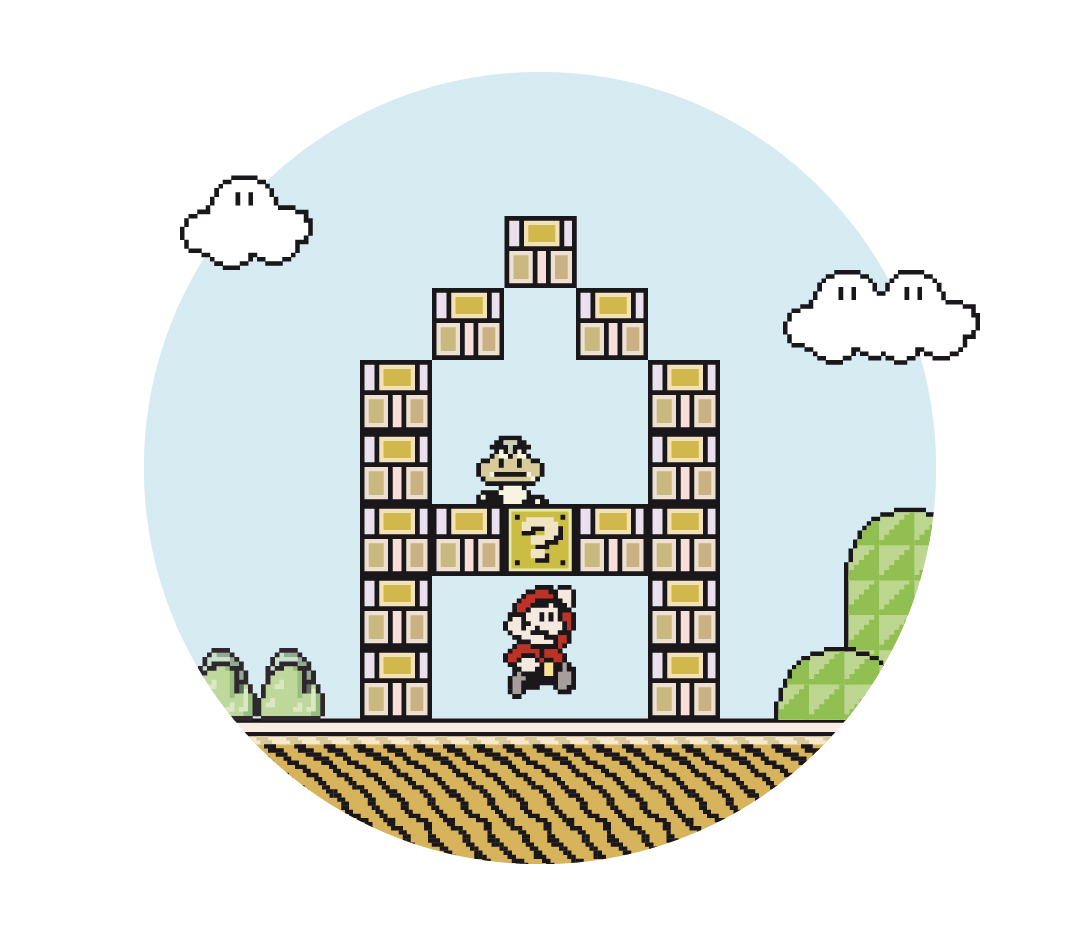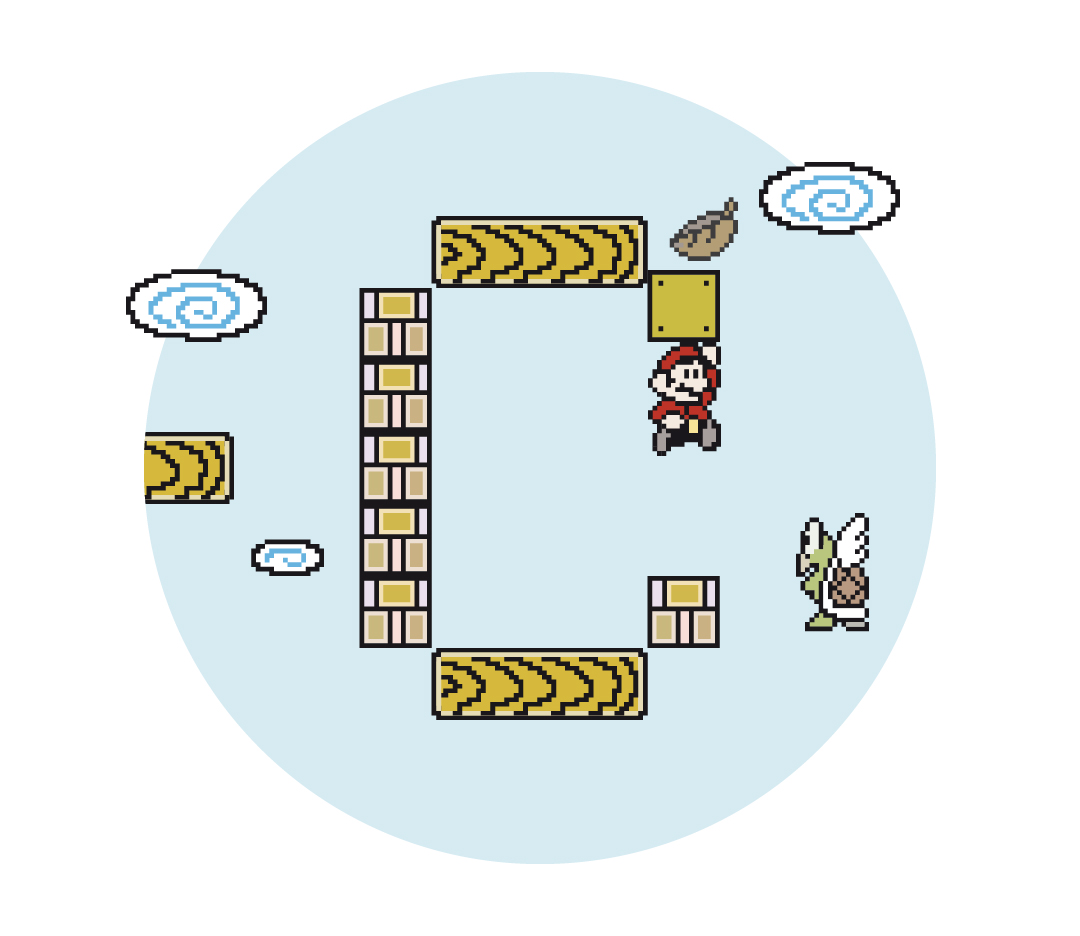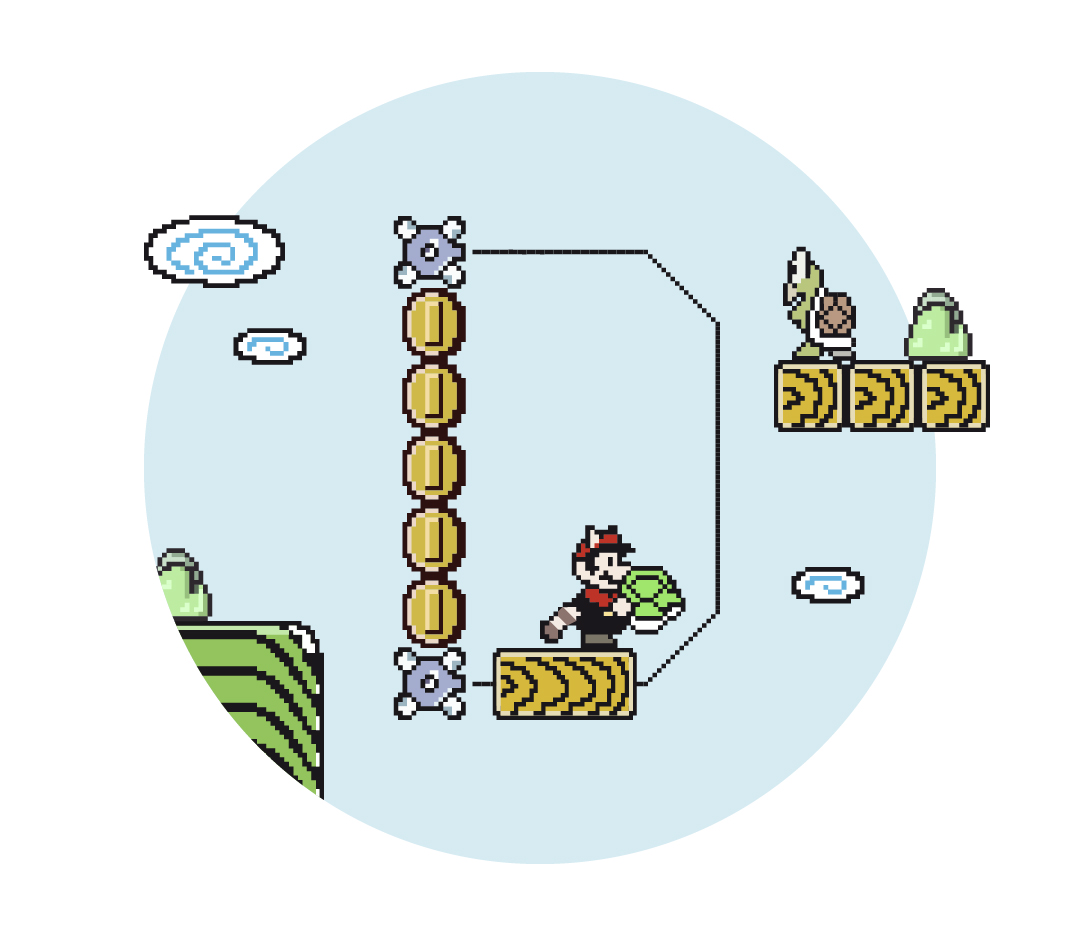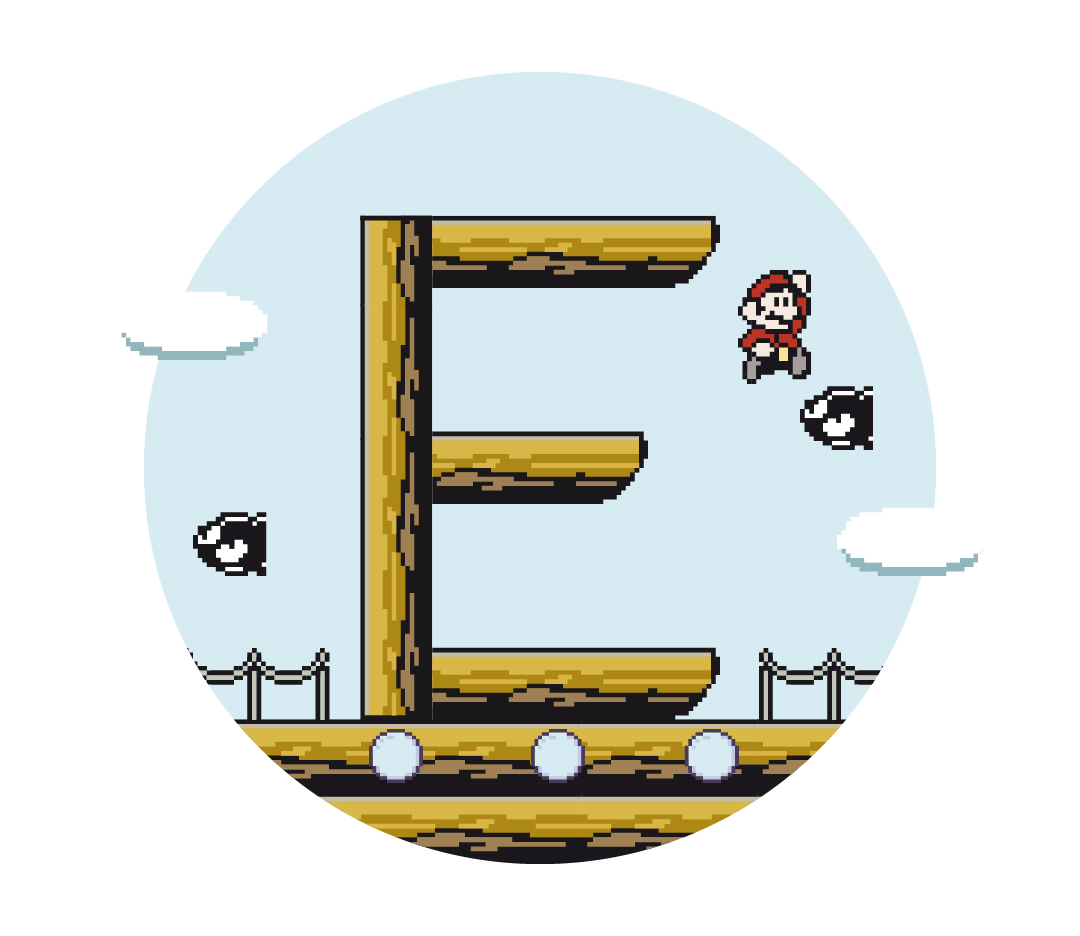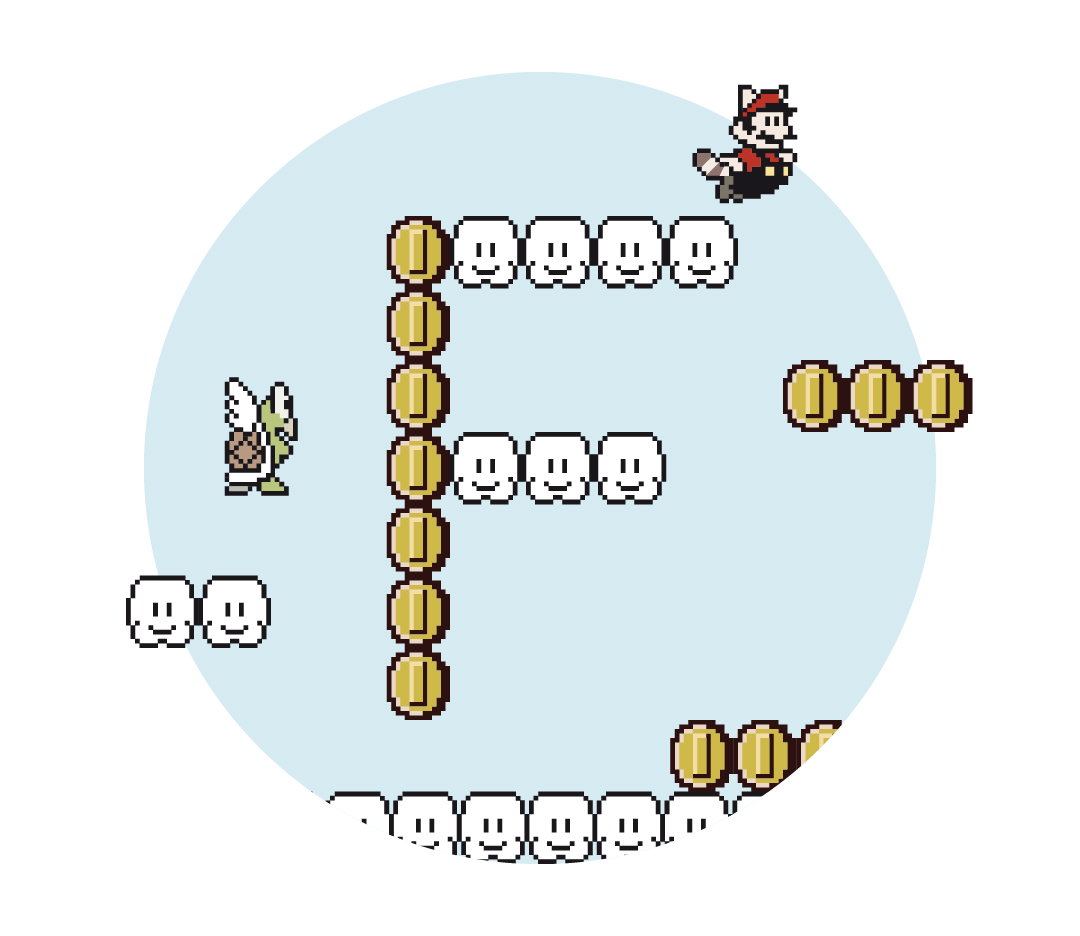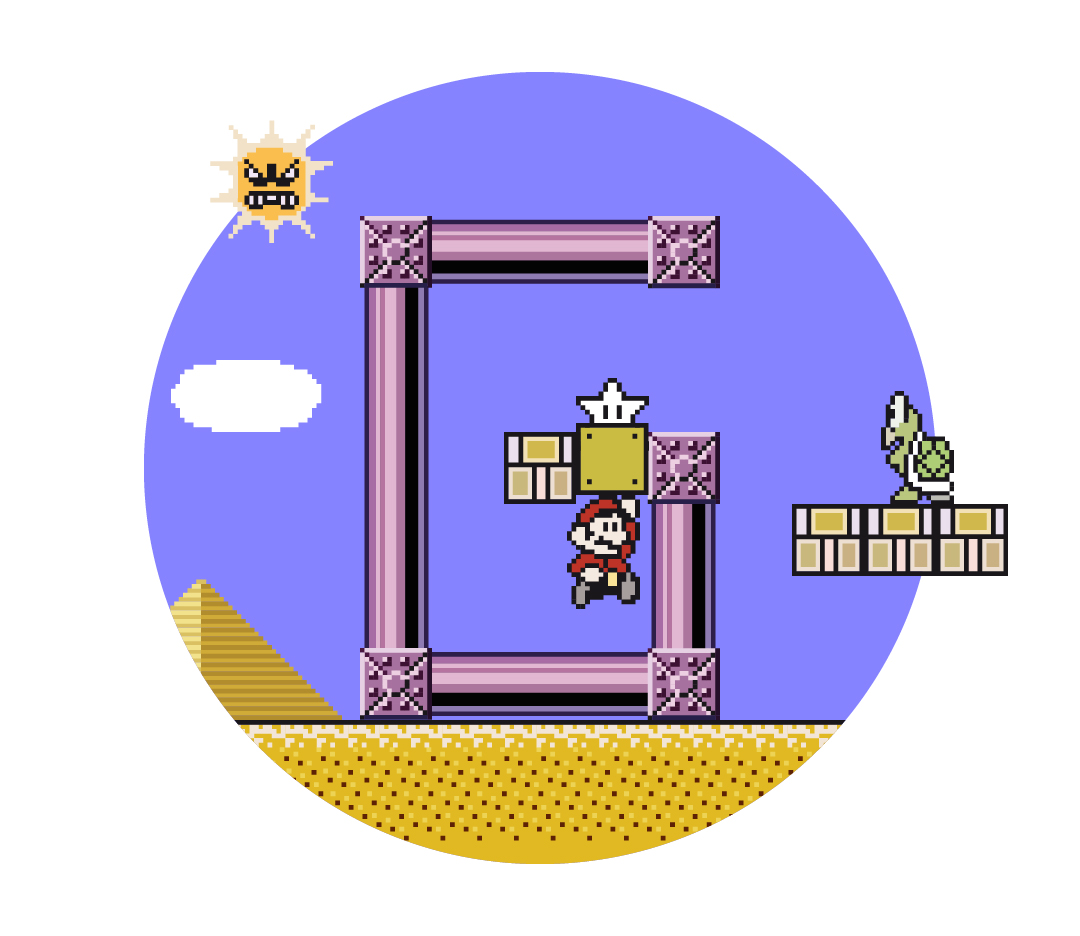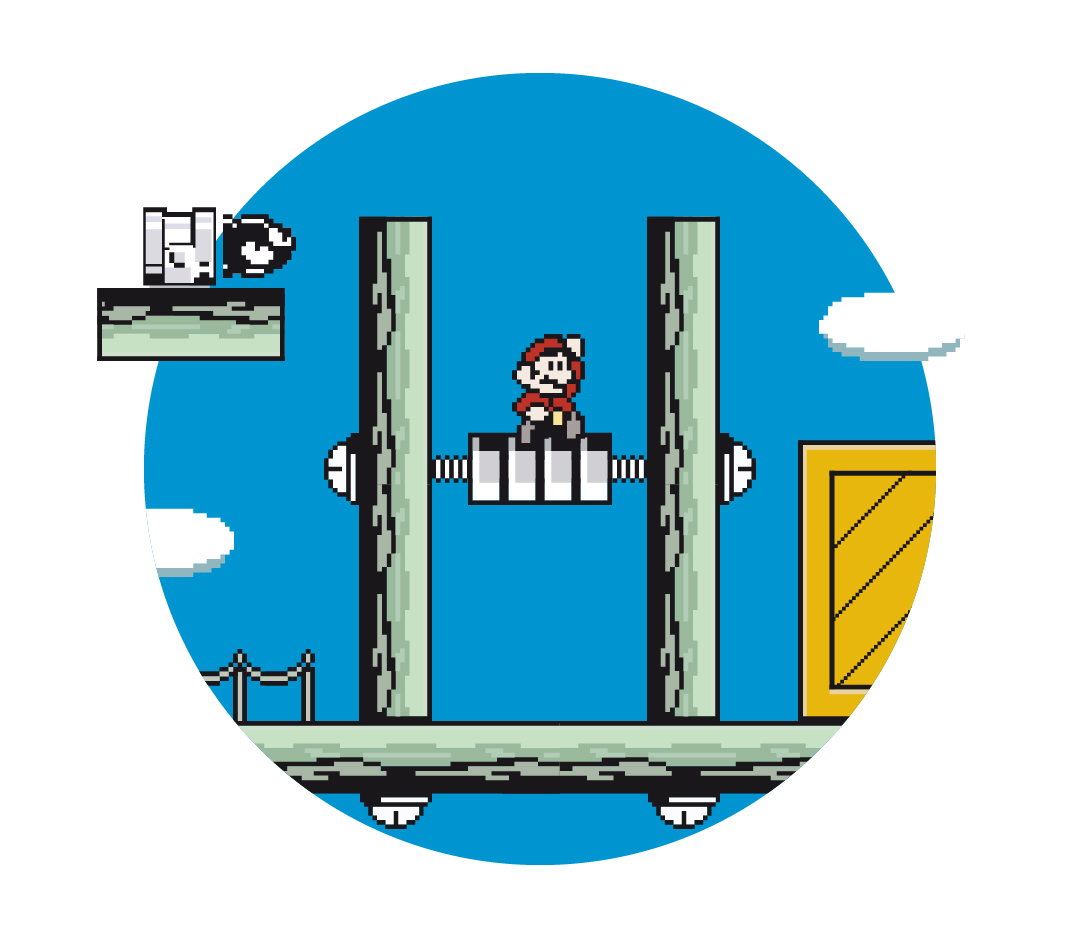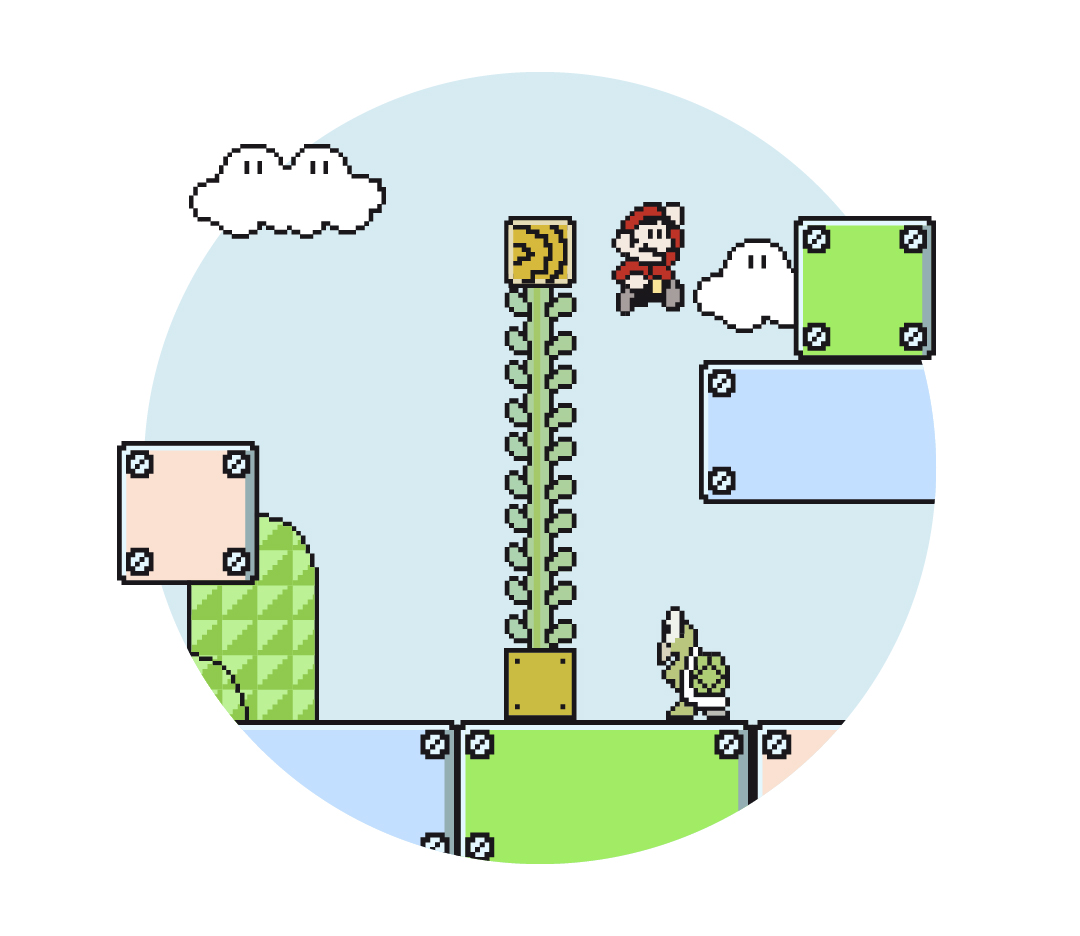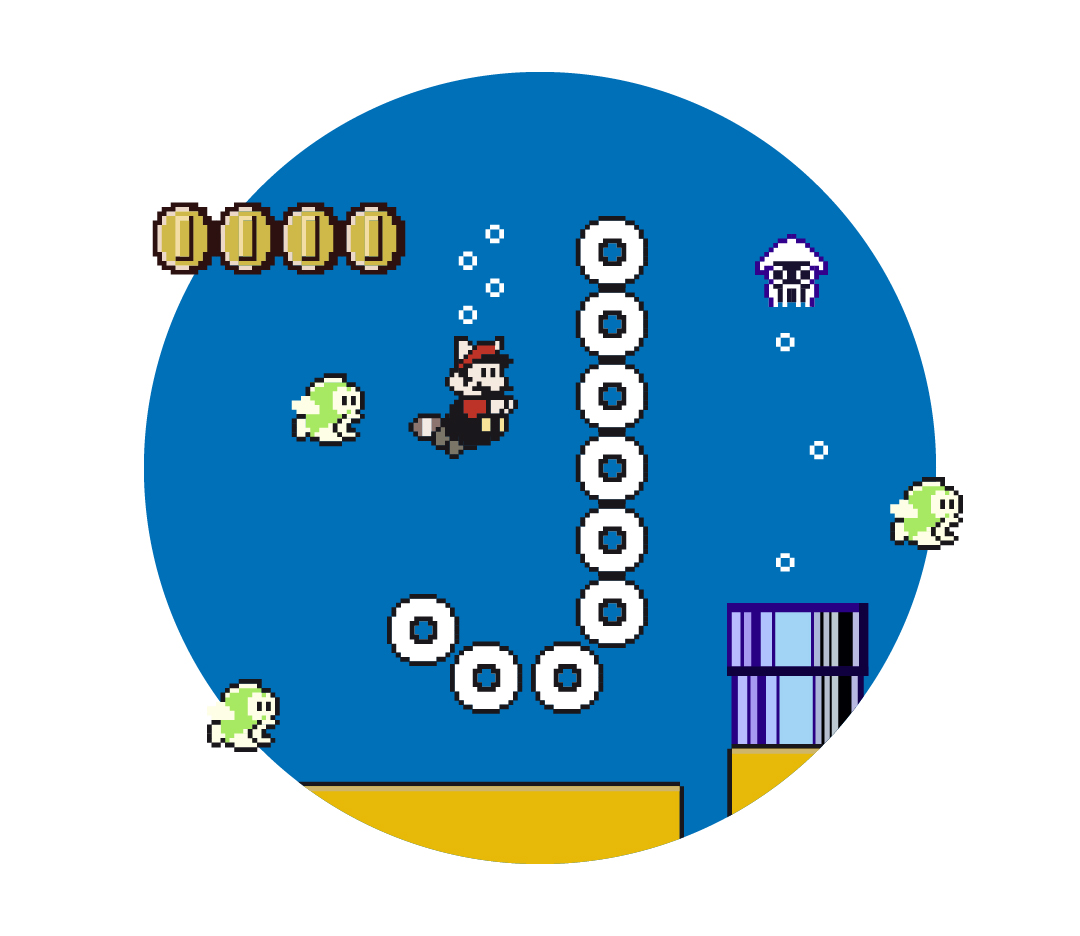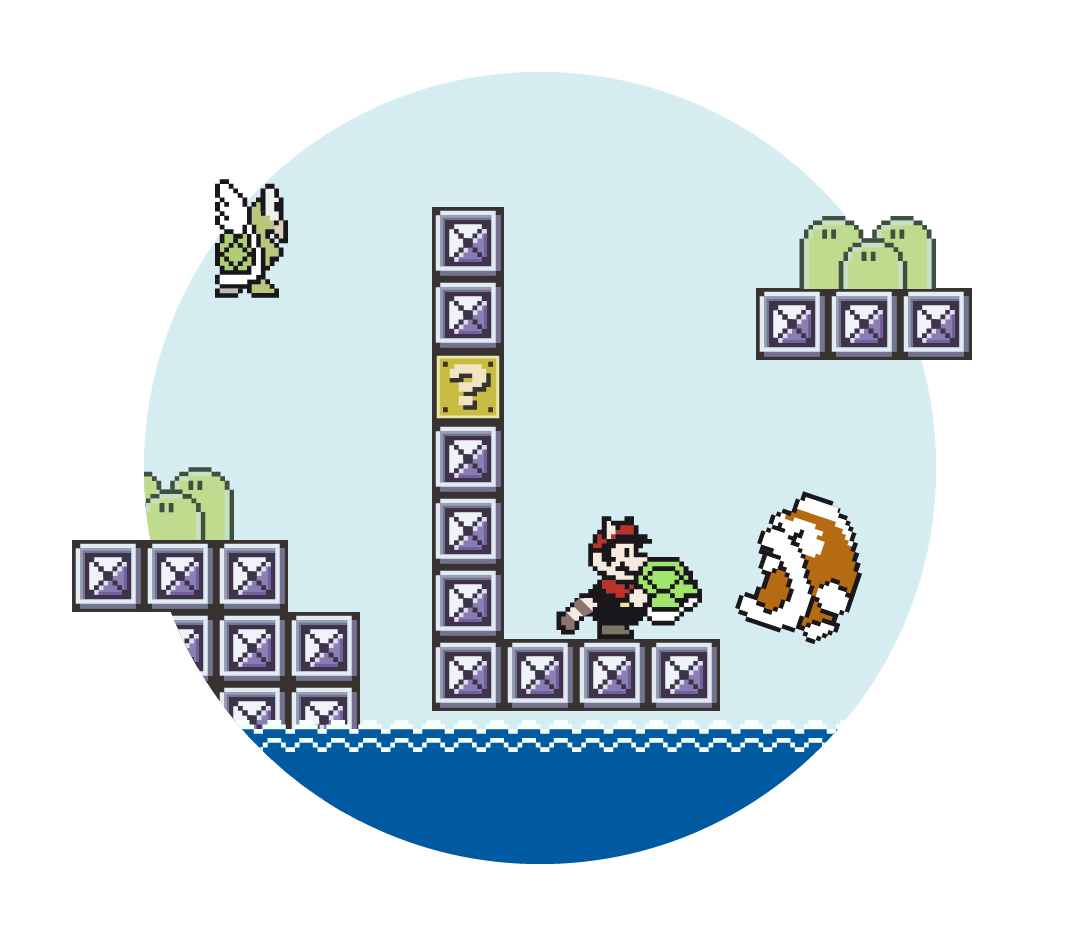
Super Mario Font
El director de arte milanés Francesco Basile se ha dado un paseo por el universo Super Mario Bros. y ha construido (o quizá se la ha encontrado escondida entre los distintos mundos, quién sabe…) una curiosa tipografía a partir de algunos de los elementos más conocidos de sus escenarios: monedas, bloques, tuberías y demás objetos inanimados se convierten ahora en astas, perfiles o vértices de estas letras-obstáculo que prometen darle mucha guerra al fontanero bigotón mientras acude al rescate de la Princesa Peach.